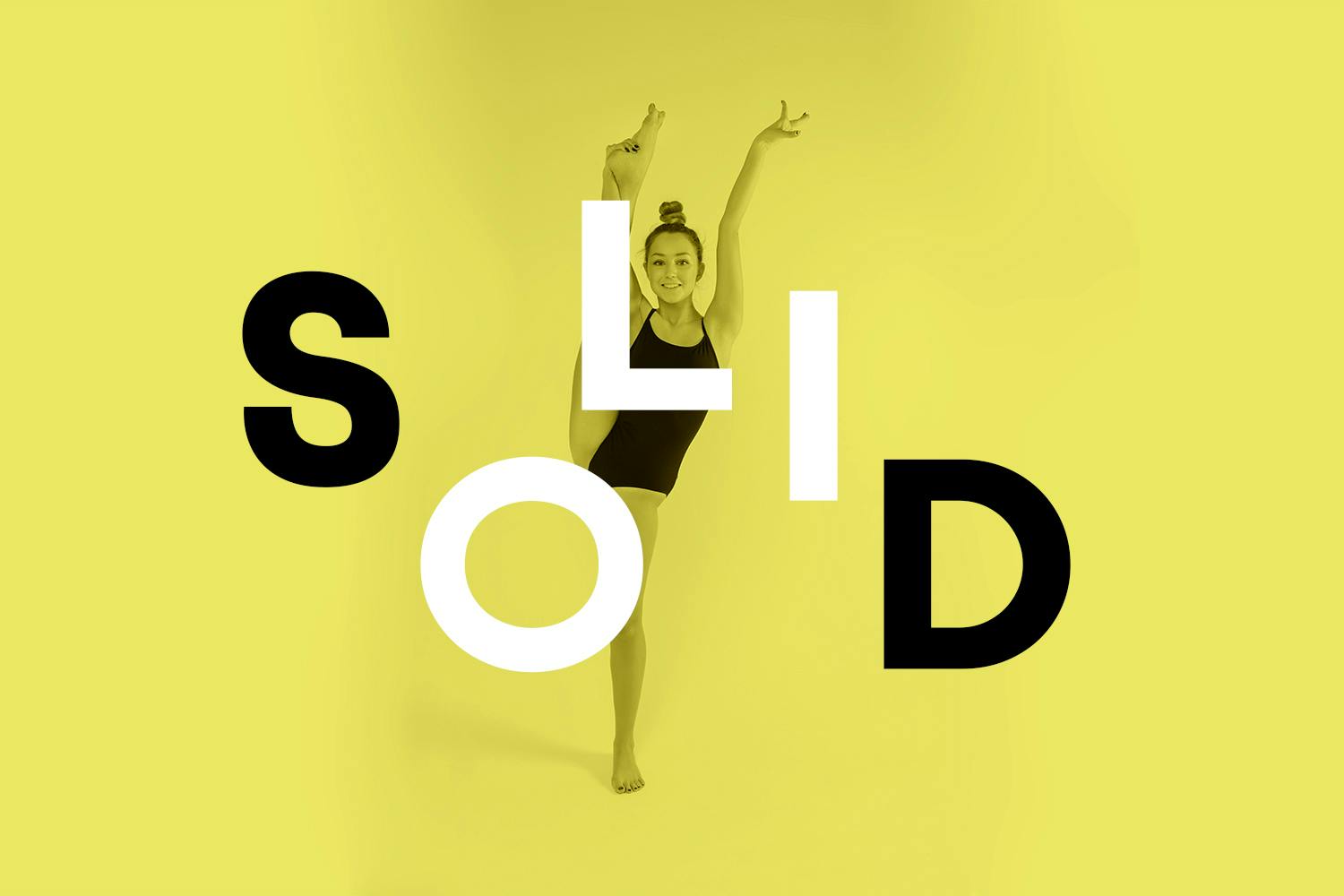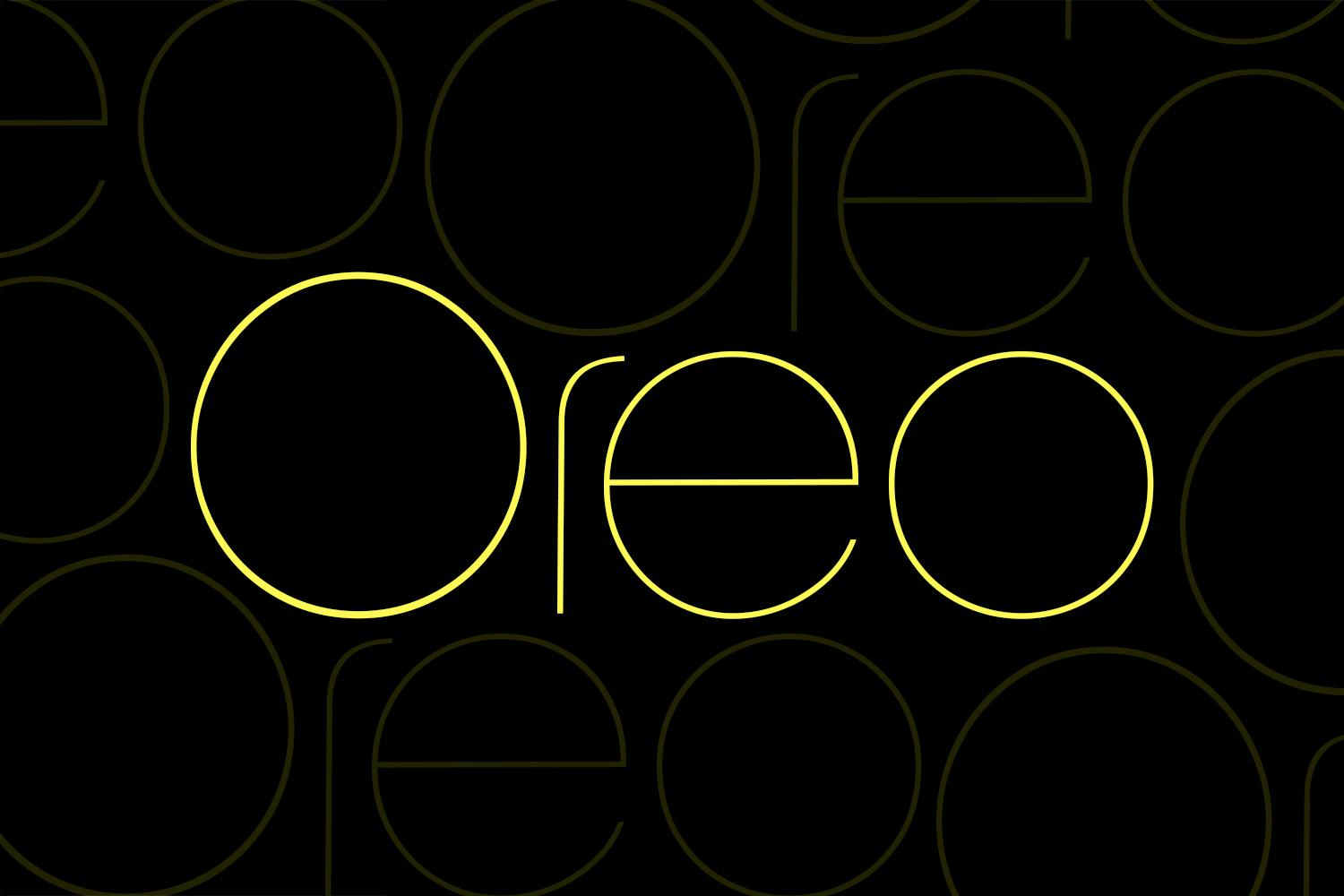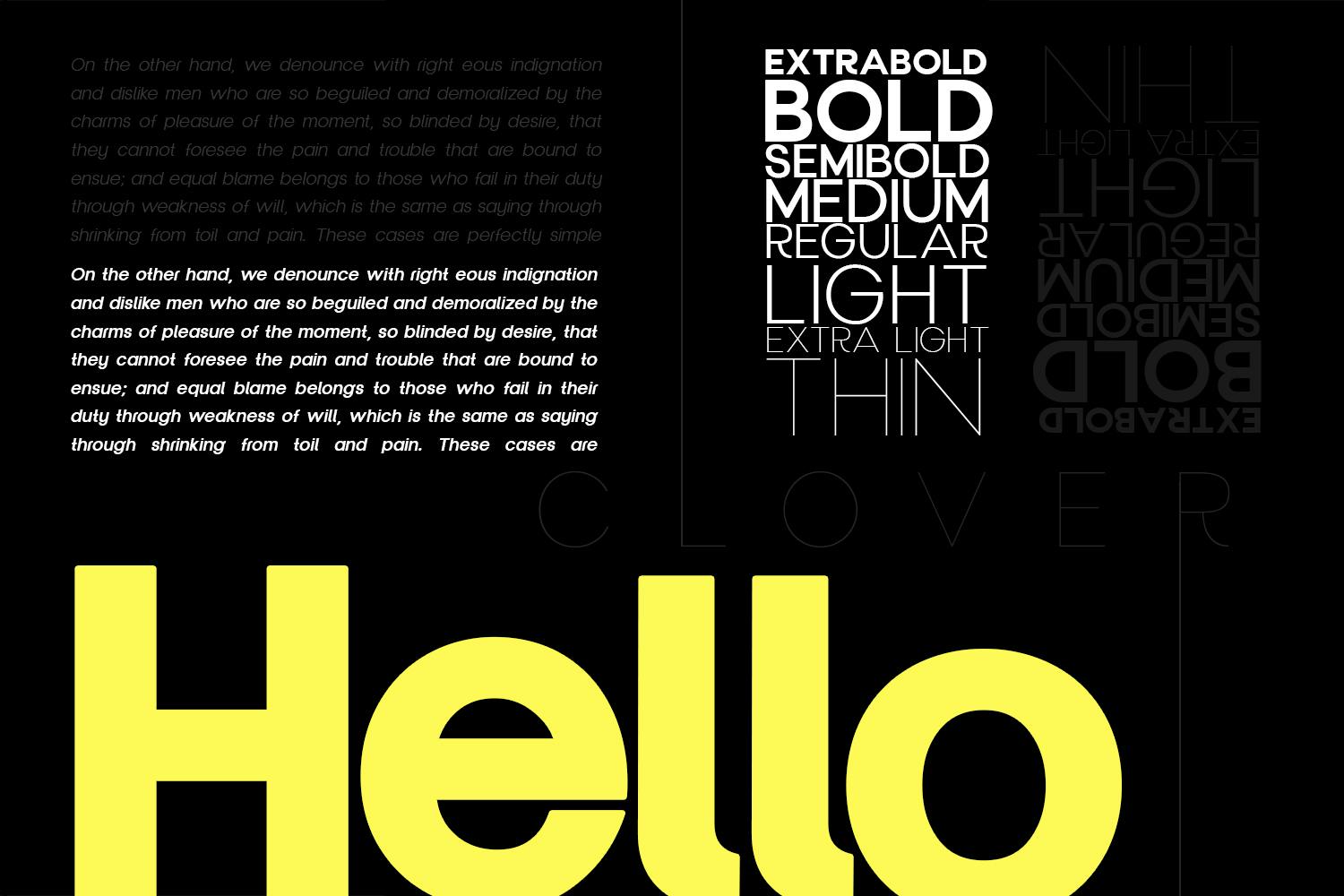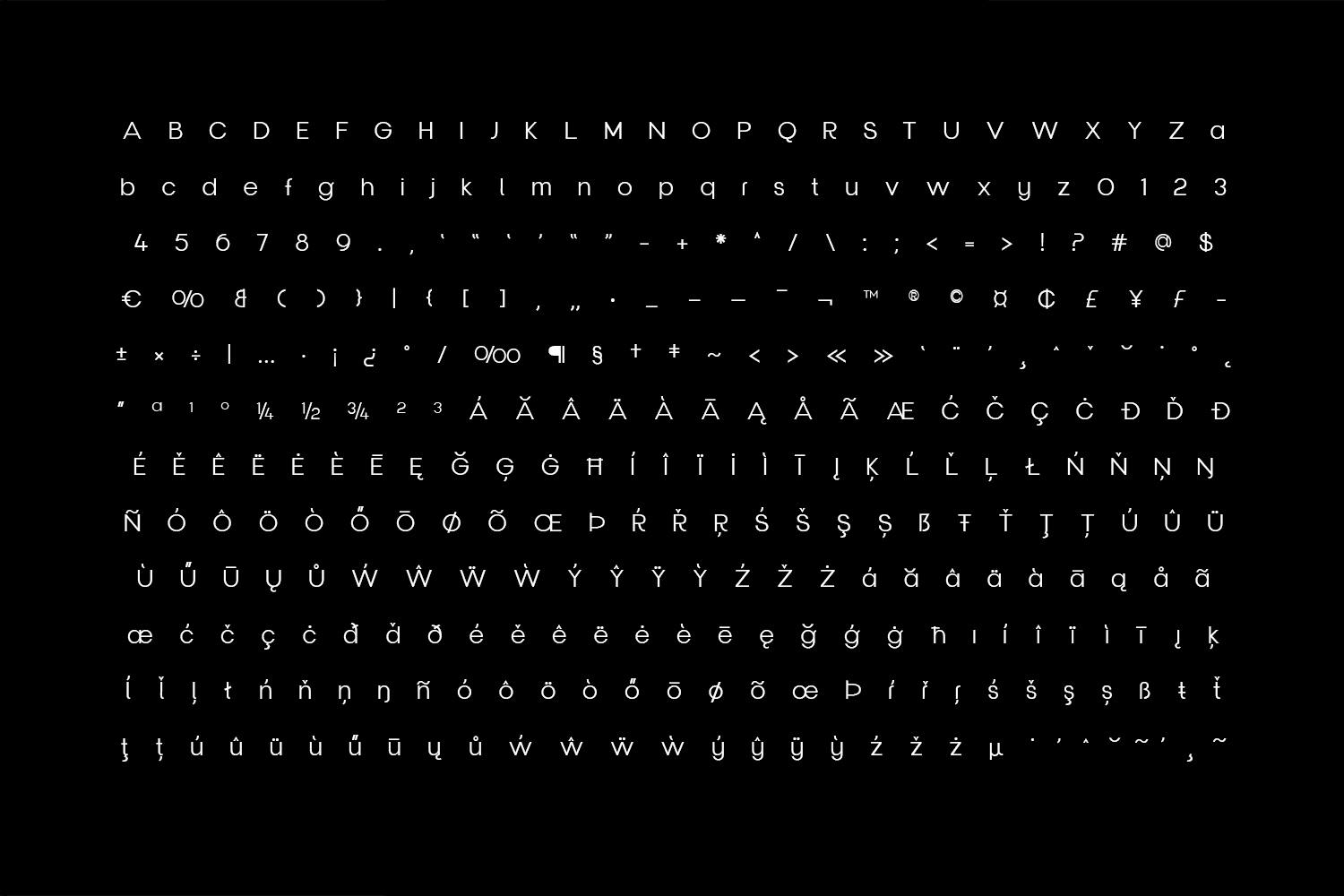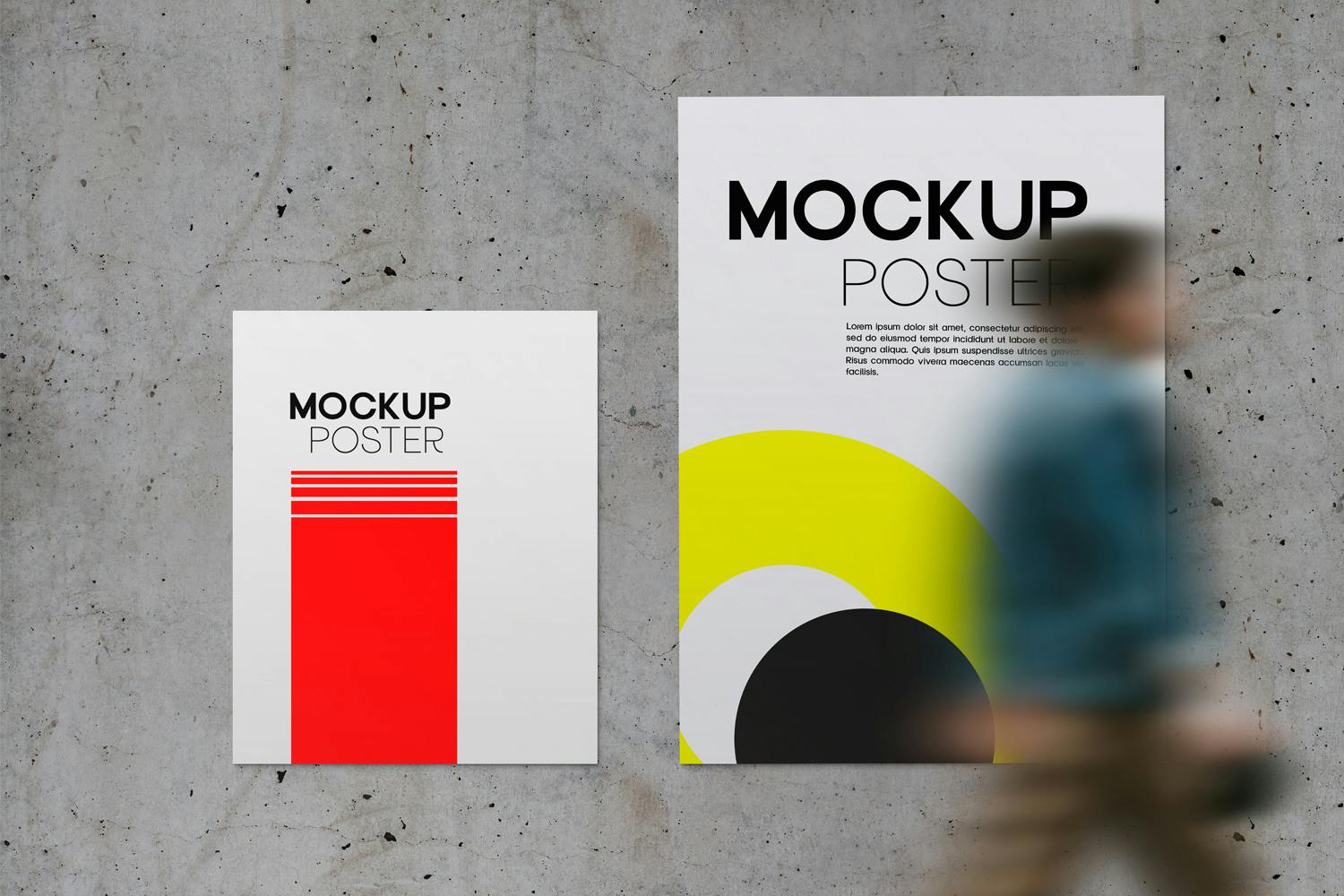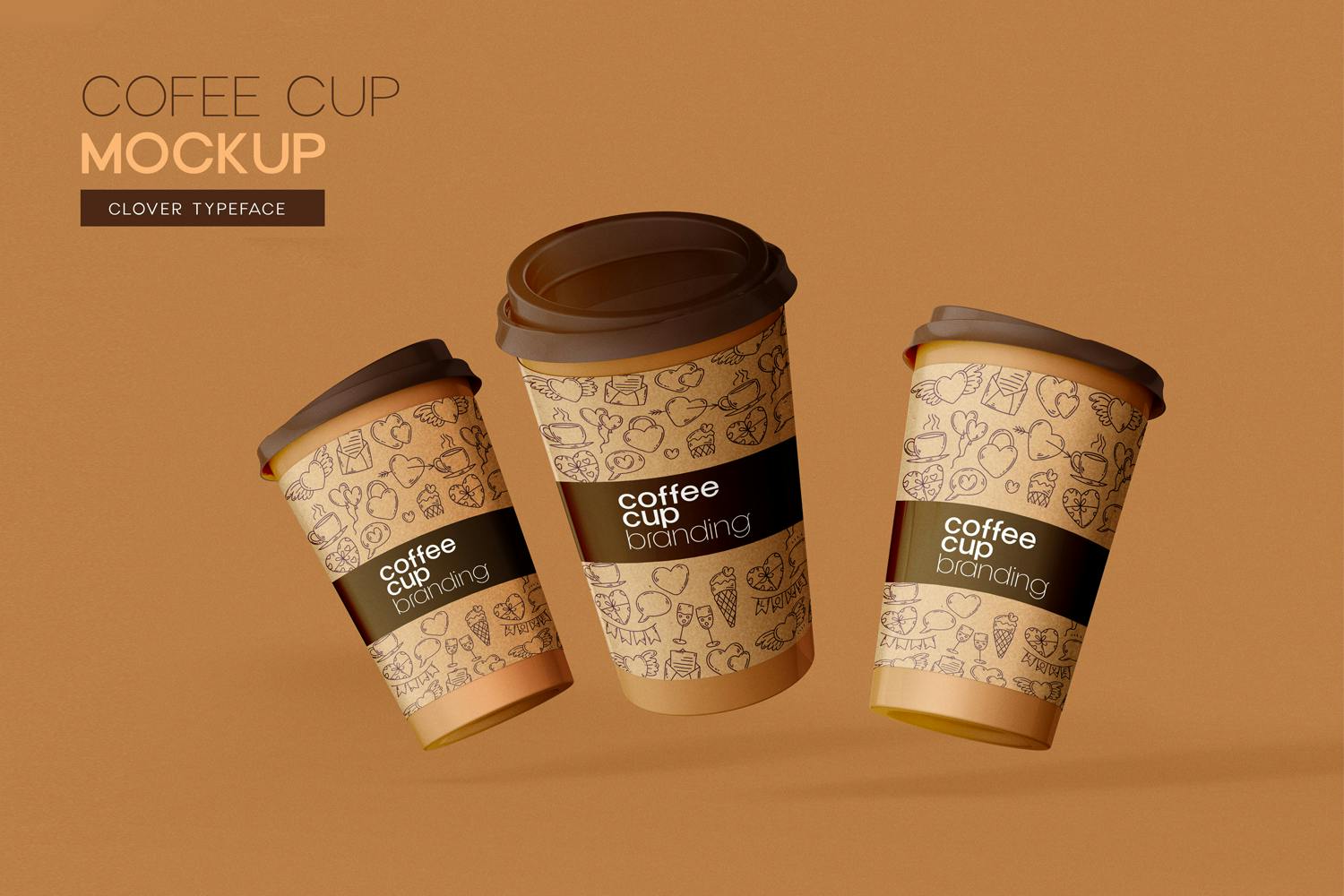
Clover Display یک فونت مدرن و منحصر به فرد با طراحی ظریف است که از خانواده Olive Typeface مشتق شده است. این فونت بسیار چندمنظوره است و در اندازههای بزرگ و کوچک به خوبی عمل میکند. فونت Clover برای برندسازی، لوگوها، عنوانها، زیرنویسها، پاراگرافها، جلد مجلات و پوسترهای فیلم بسیار مناسب است و میتواند به عنوان یک پوشش متنی شیک بر روی هر تصویر پسزمینهای استفاده شود. حروف بزرگ قوی و حروف کوچک نرم و باز در کاربردهای مختلف مؤثر هستند. این فونت طراحی تمیز، مینیمالیستی و گرم دارد و در عین حال خاص و آسان برای خواندن است.
فونت Clover با ۰۸ وزن و ۱۶ استایل (شامل ایتالیک) طراحی شده است.